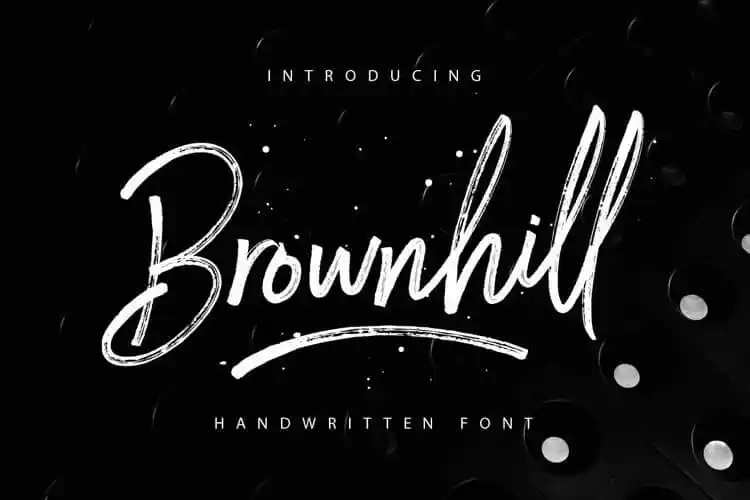
Brownhill Brush Font – Download Grátis
A fonte Brownhill Brush é uma escolha ideal para designers atentivos à qualidade e estilo. Desenvolvida pelo designer 99designs, ela representa uma tipografia script autêntica que se sobressai pela sua natureza casual e rápida de escrita. As letras são criadas a partir do uso de pincéis sobre papel, resultando em um design versátil e elegante que se adapta perfeitamente para um amplo range de projetos gráficos. Ideal tanto para criação de logotipos e cartões de nome, como para impressão de citações escritas a mão ou qualquer outro produto que seja criado à partir de uma frase ou texto, esta fonte oferece um design rápido e fácil na produção de produtos. Ela contém uma completa gama de letras maiúsculas e minúsculas, sinais linguísticos, números e suporta múltiplas línguas, tornando-a perfeita para todos os profissionais do design que buscam aperfeiçoar sua capacidade de criar obras finamente detalhadas.